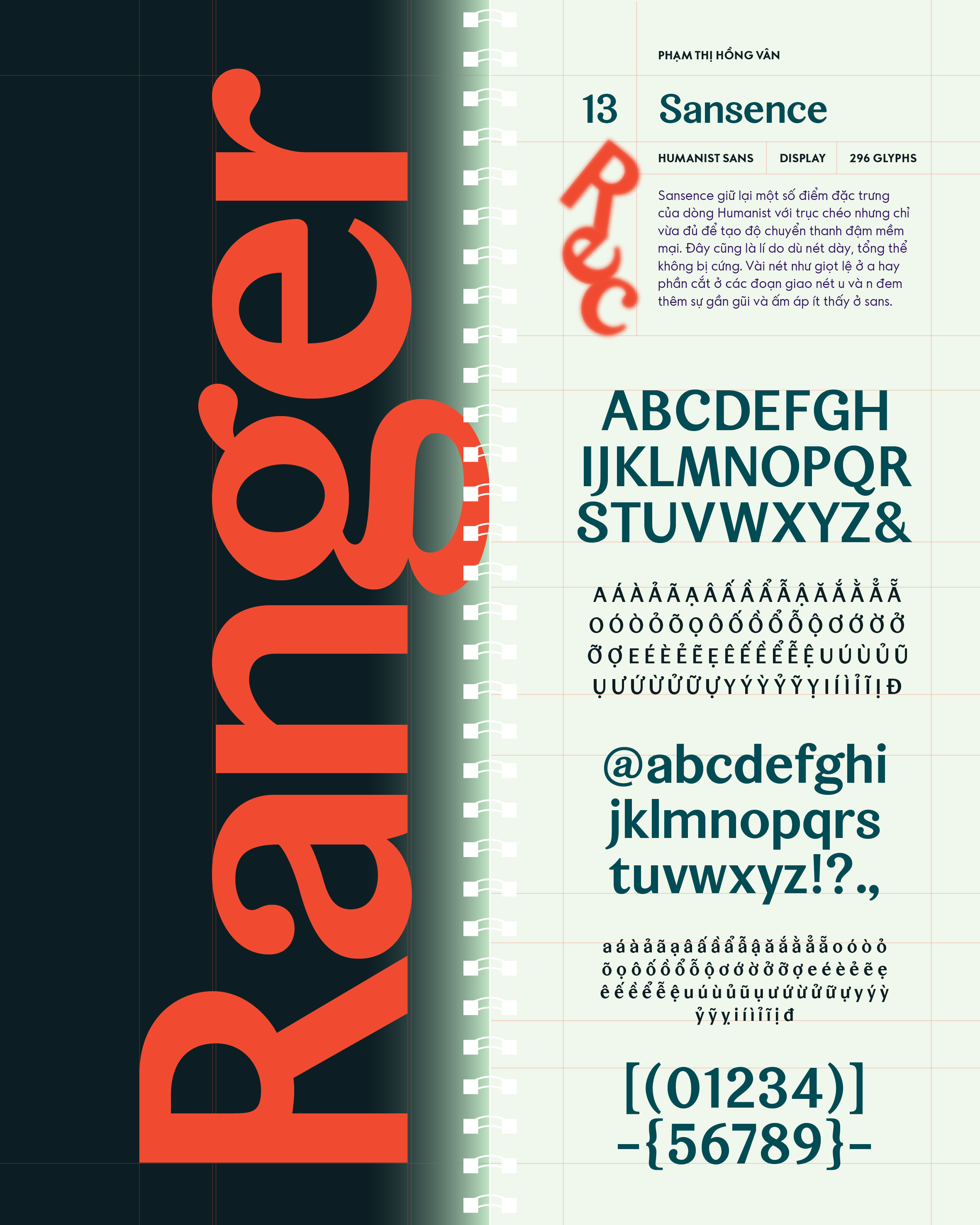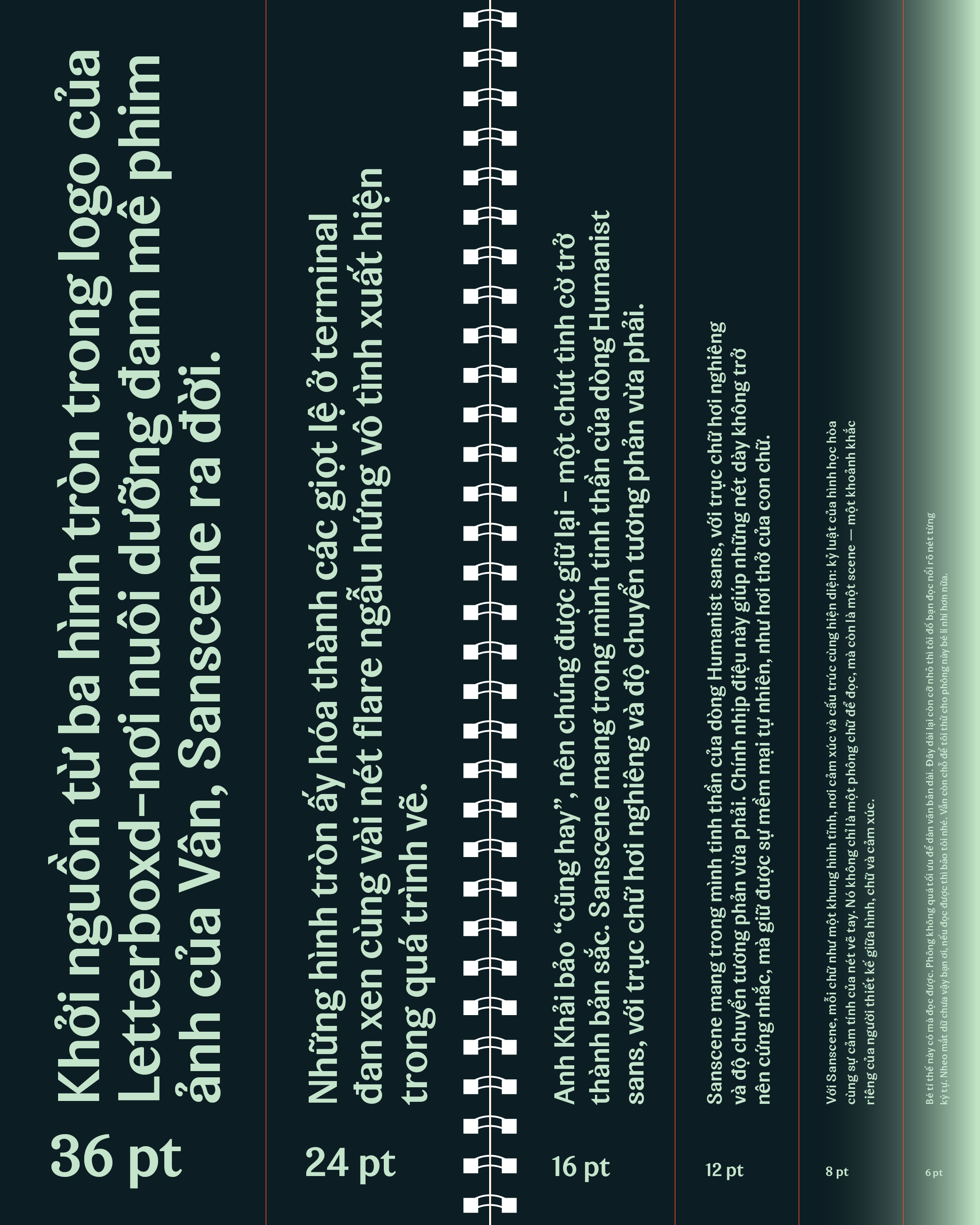
Sansence
Về Sansence: Sansence giữ lại một số điểm đặc trưng của dòng Humanist với trục chéo nhưng chỉ vừa đủ để tạo độ chuyển thanh đậm mềm mại. Đây cũng là lí do dù nét dày, tổng thể không bị cứng. Vài nét như giọt lệ ở a hay phần cắt ở các đoạn giao nét u và n đem thêm sự gần gũi và ấm áp ít thấy ở sans.
Humanist Sans-serif
Display
Phạm Thị Hồng Vân